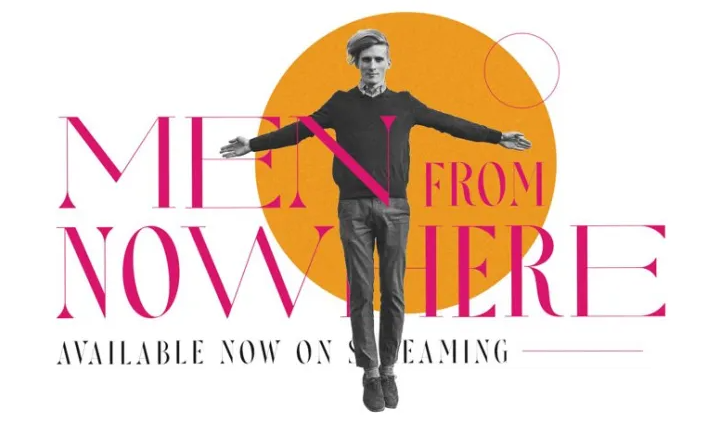
Nefarious - уникальный и современный шрифт с засечками.
Благодаря расширенной версии в виде строчных букв, этот шрифт сделает вашу презентацию, плакат, логотип или обложку журнала еще более потрясающей и выделяющейся с помощью простых шагов! Вы можете смешивать и сочетать прописные и строчные буквы для создания современного образа. Этот шрифт поддерживает несколько языков.